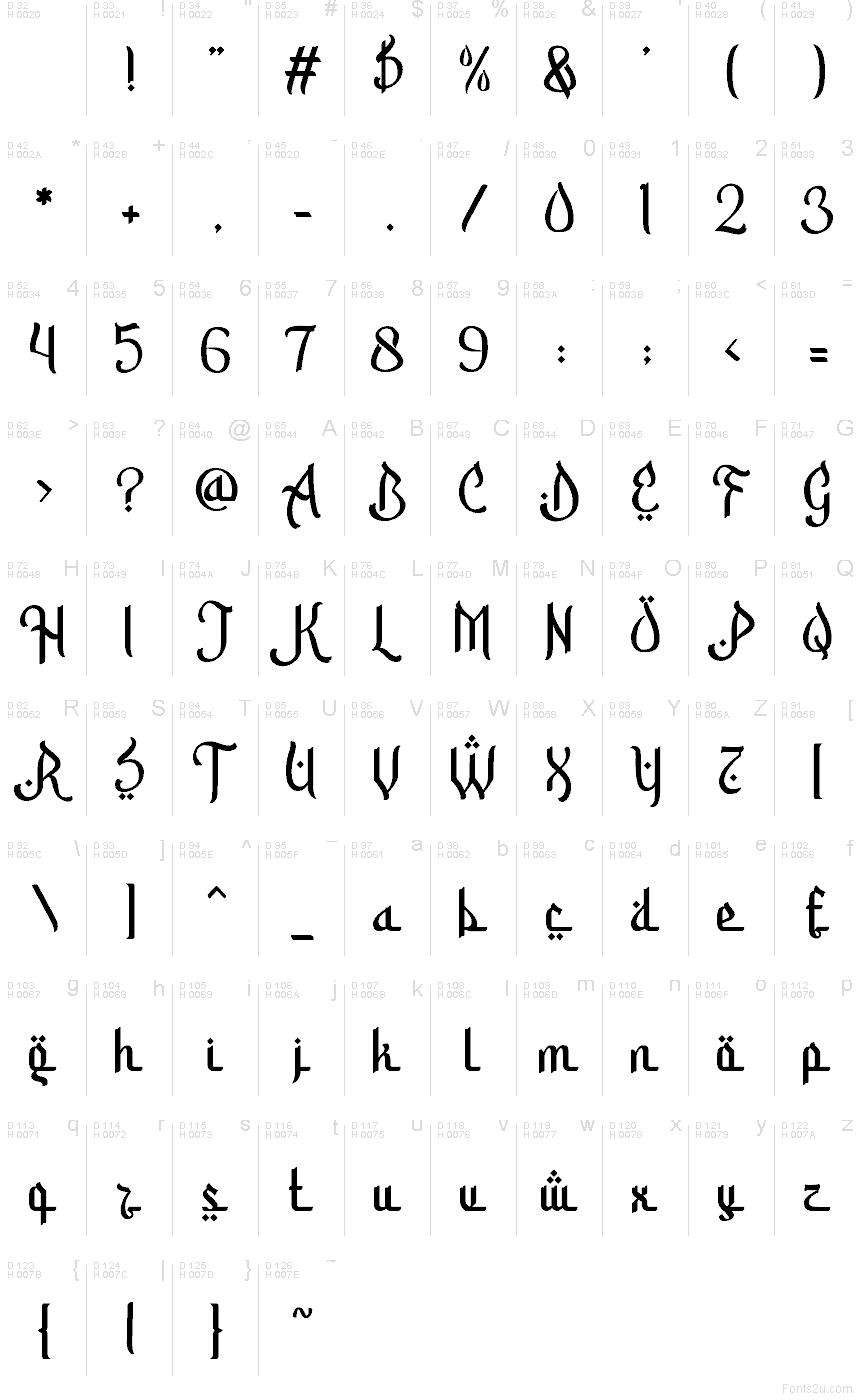
Majidi Mirage
Majidi Mirage od Putracetol Studio je bezplatné akcidenčné písmo inšpirované arabskou estetikou, ktorému dominujú vysoké zvislé ťahy, zúžené krivky a drobné kosoštvorcové akcenty v znakoch. Táto opakujúca sa silueta dodáva dizajnu kaligrafický nádych, kde ostré zvislice a zaoblené tvary vytvárajú úzky, obradný rytmus, ktorý sa líši od bežných, neutrálnych písiem.
Ideálne sa hodí pre vizuálnu identitu reštaurácií, obaly parfumov, plagáty na akcie, grafiku hudobných albumov a označenie butikov, kde tento štylizovaný arabský odkaz okamžite určuje tón. Špicaté vrcholy a kompaktné vnútorné krivky navyše dodávajú krátkym titulkom a monogramom vycibrený, emblémový vzhľad, ktorý pôsobí oveľa remeselnejšie než bežná typografia.